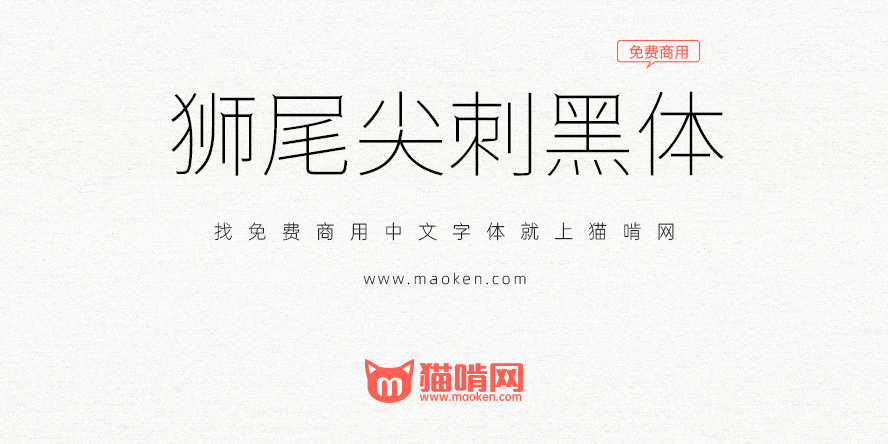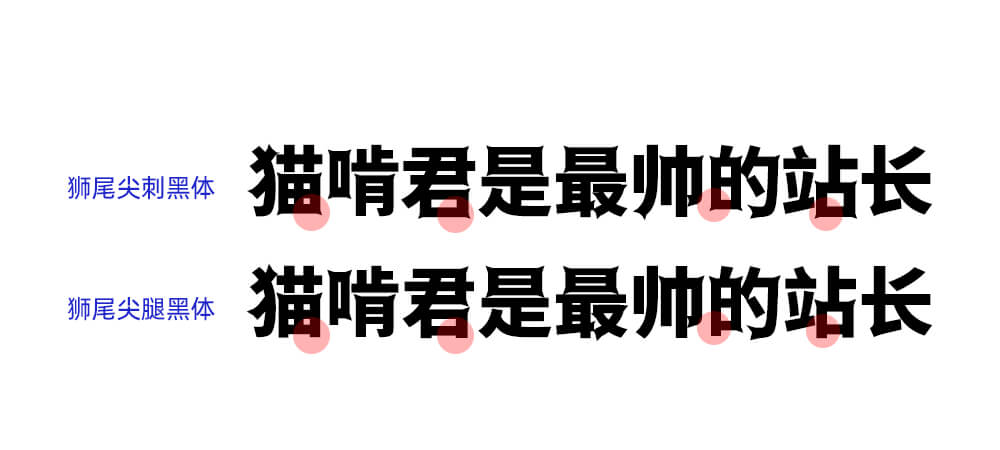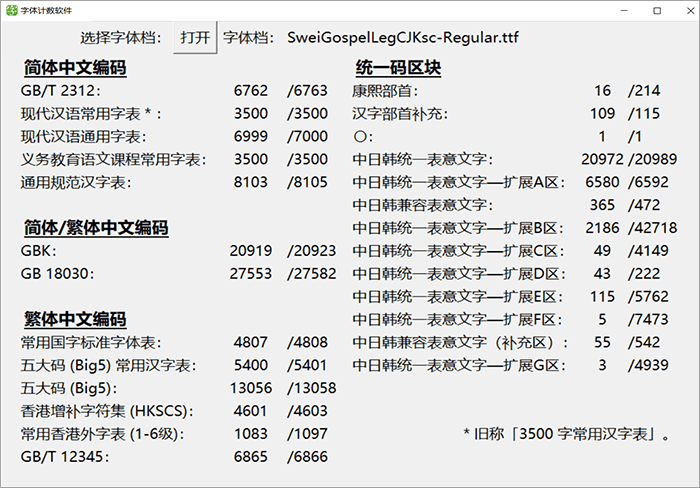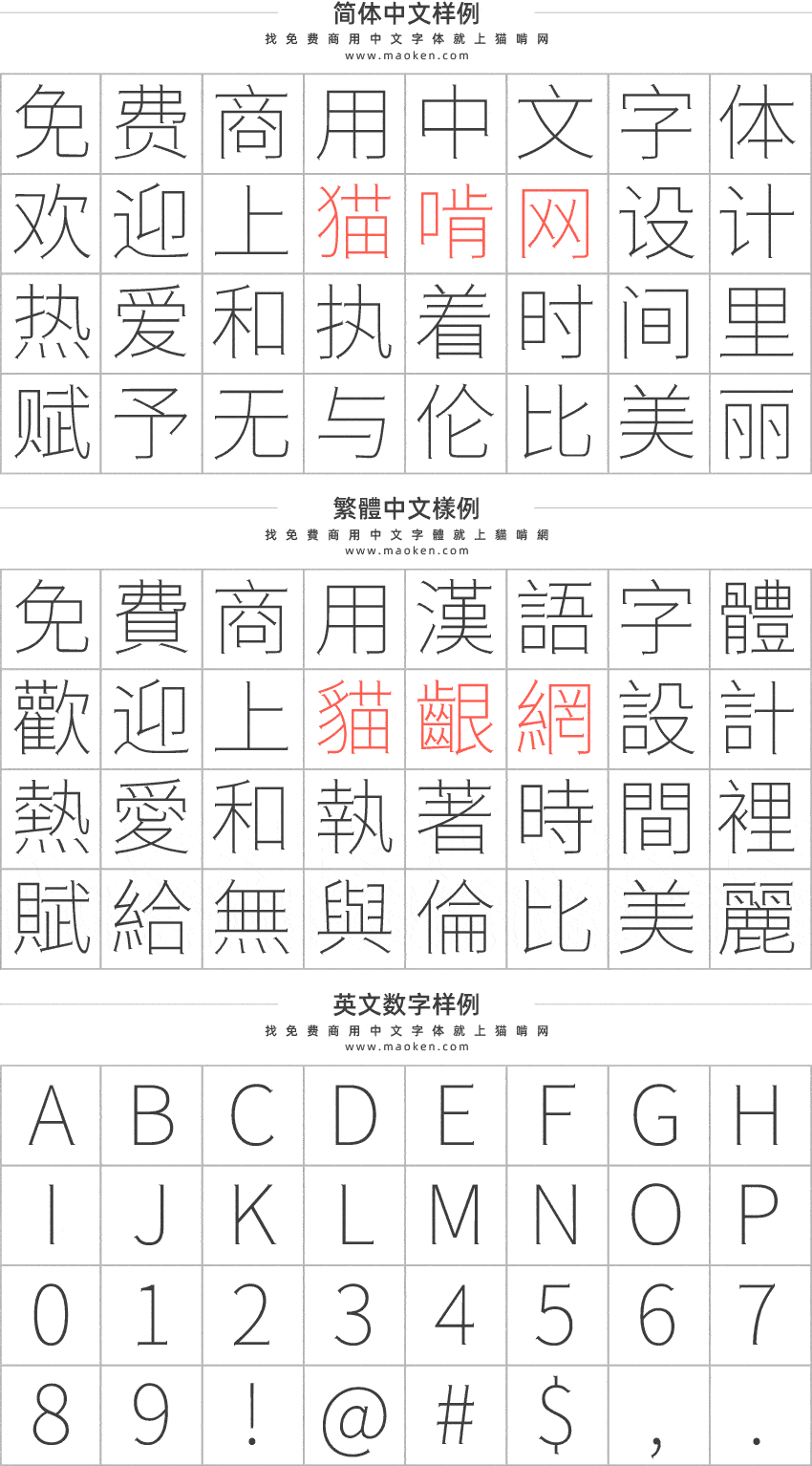
狮尾尖刺黑体基于思源黑体的转角长尖刺和拔脚改造,更加简明现代化的字体。支援简体中文、繁体中文、韩文与日文;可以免费商用,欢迎大家自由应用、自由优化、自由改作!
狮尾尖刺黑体的特色是,「口」字的4个转角长尖刺。
「狮尾尖腿黑体」与「狮尾尖刺黑体」差别在有没有拔脚,「拔脚」就是会有较少的笔画,例如移除「口」字的左右下角会多出的短线条。有拔脚的字会较圆,但是会造成有些字因直接去掉腿后左右不平衡、左右不对衬的「悬空」问题。改使用「腿」系列字体就不会有这个问题。